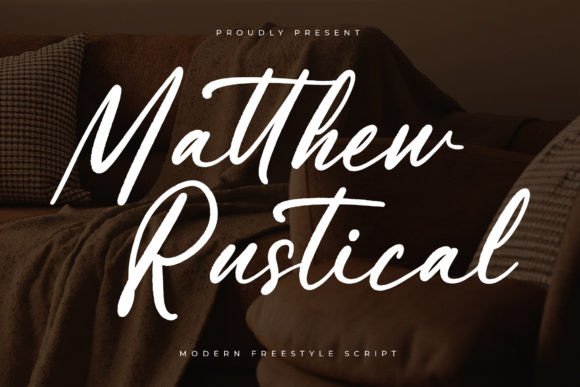
Matthew Rustical
Wenn Sie nach hochwertigen Assets wie Matthew Rustical suchen, ist dieses Premium-Paket eine fantastische Wahl für Ihre kreativen Projekte.
Egal, ob Sie POD-Produkte (Print on Demand), Hochzeitseinladungen oder Social-Media-Grafiken erstellen, Matthew Rustical ist die ideale Wahl.